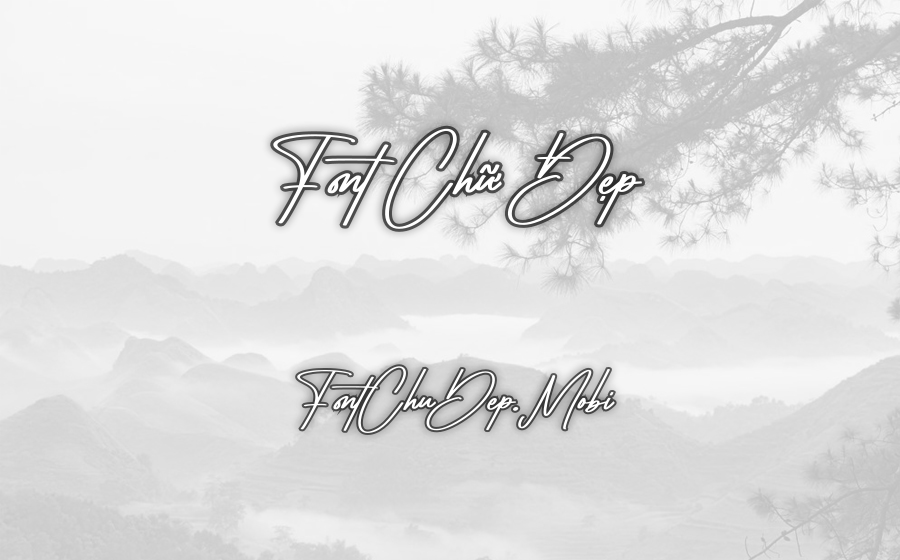
Font SVN Blywoofs Việt Hóa
SVN Blywoofs
Font chữ Blywoofs thực sự là một lựa chọn thú vị và độc đáo mà tôi đã có dịp trải nghiệm. Điểm nổi bật nhất của Blywoofs chính là phong cách viết tay tự nhiên kết hợp với nét vẽ đậm và vui mắt. Font này mang lại cảm giác ấm cúng, thân thiện, tạo sự gần gũi ngay từ cái nhìn đầu tiên.
Một trong những ưu điểm lớn nhất của Blywoofs là khả năng hỗ trợ đa ngôn ngữ. Với hơn 100 ngôn ngữ được hỗ trợ, Blywoofs thực sự mở rộng tầm sử dụng của nó trên toàn cầu. Đặc biệt, Styleno.1 Fonts đã chăm chút Việt hóa font này, giúp cộng đồng thiết kế Việt Nam dễ dàng tích hợp Blywoofs vào các dự án sáng tạo của mình. Bên cạnh đó, việc được tìm kiếm và chia sẻ bởi FontChuDep.mobi càng làm tăng thêm giá trị của font chữ này đối với những ai đang tìm kiếm sự mới lạ.
Thiết kế của Blywoofs mang đến sự linh hoạt và sáng tạo hiếm có. Những đường nét viết tay đậm, tự nhiên là yếu tố then chốt giúp Blywoofs trở thành lựa chọn lý tưởng cho các dự án như thiết kế logo, truyền thông xã hội, tiêu đề phim, bìa sách và nhiều văn bản ngắn khác. Đặc biệt, Blywoofs thực sự tỏa sáng trong những lĩnh vực như quảng cáo, nghệ thuật và thiết kế đồ họa, khi cần đến sự phá cách và sáng tạo không giới hạn.
Nhìn chung, nếu bạn đang tìm kiếm một font chữ có thể vừa thể hiện phong cách cá nhân độc đáo vừa phù hợp với nhiều ứng dụng khác nhau, Blywoofs chắc chắn là sự lựa chọn không làm bạn thất vọng.